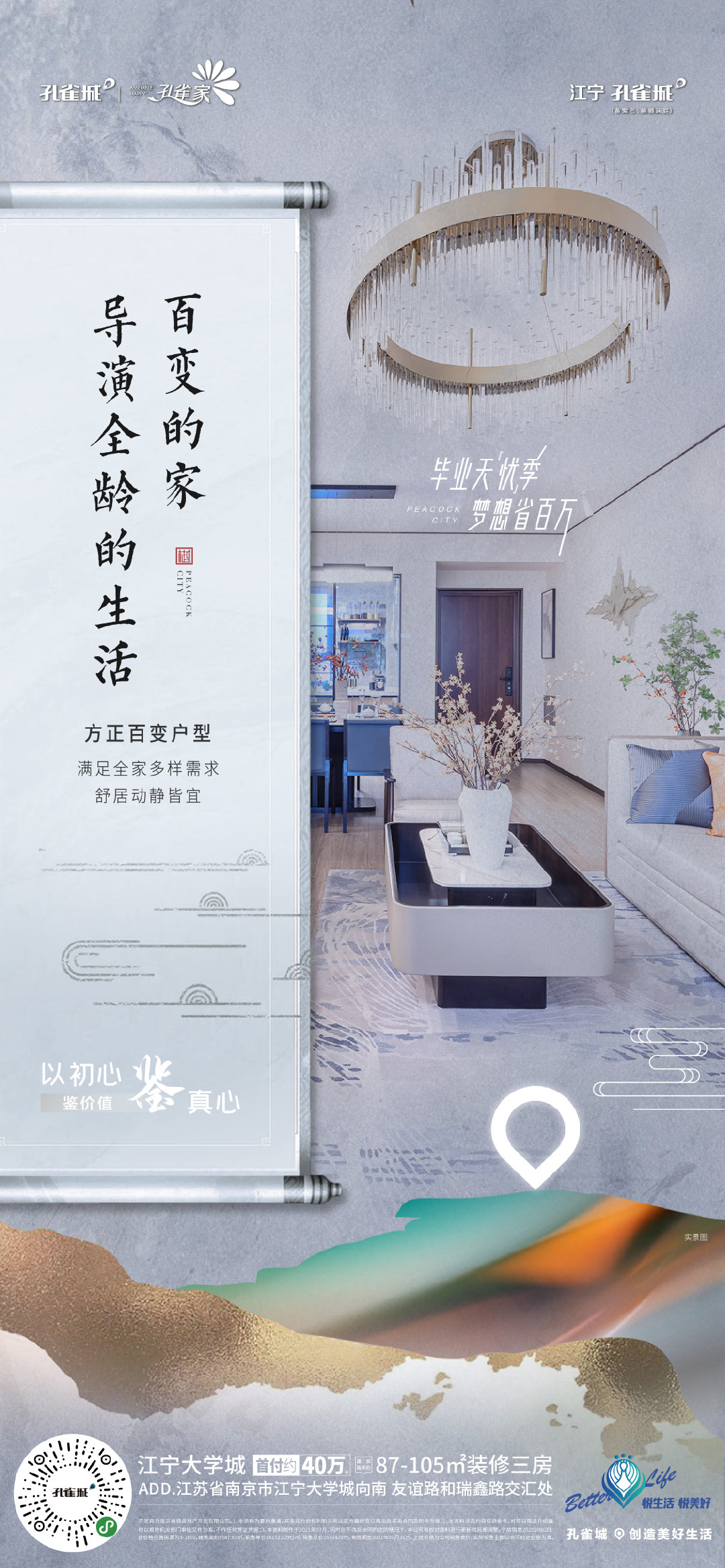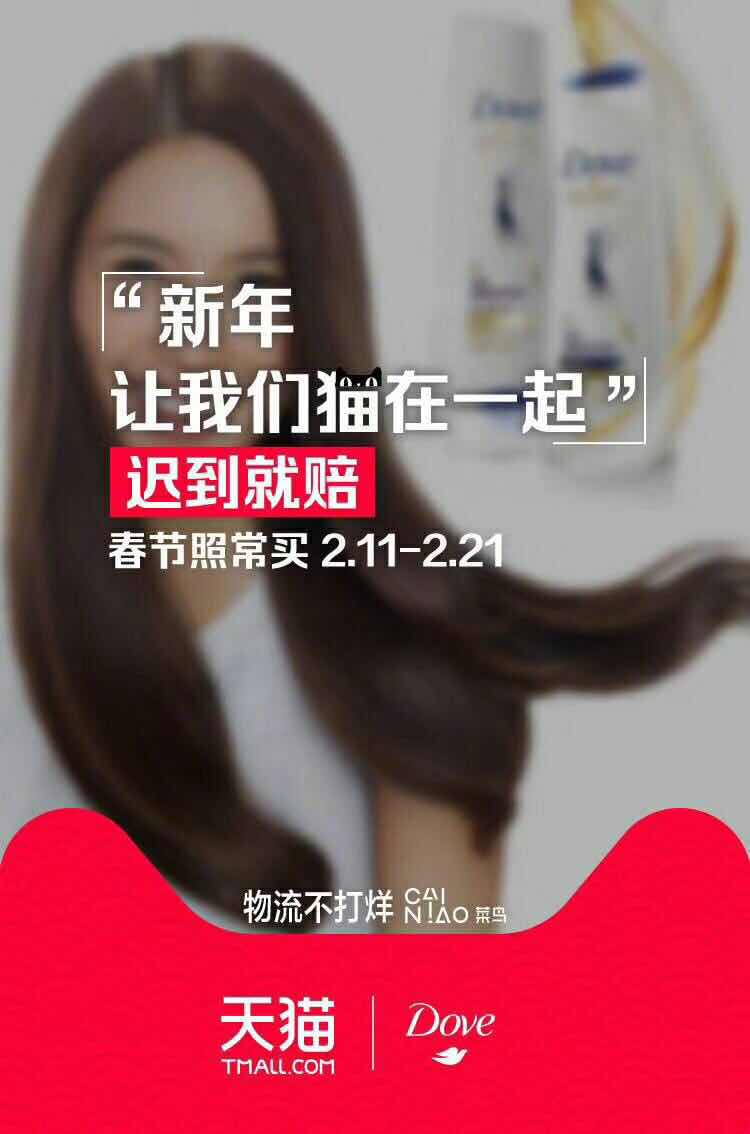
方正创黑家族
杨创,褚方敏
黑体、创意字体
这款字的创意风格来源于我们最常用的黑体字,在黑体的基础上增强了字体结构的饱满度,加强了笔画的韵律和节奏感,以及规范度让整体字形更加简洁易记同时兼备艺术感。在横竖笔画转角的处理上,加以传统书法的提笔落笔,让整体字形彰显力量感顿挫感,在撇捺笔画的走势上,借鉴了宋体字笔画的柔和度,让整体字形摒弃黑体字的生硬,让它更具优雅性, 在创作过程中,我们始终让字形兼具力量与优雅并存,从而在简洁的字形中,形成自身最大的特征。适用于产品包装、海报视频、大标题及周边等领域。